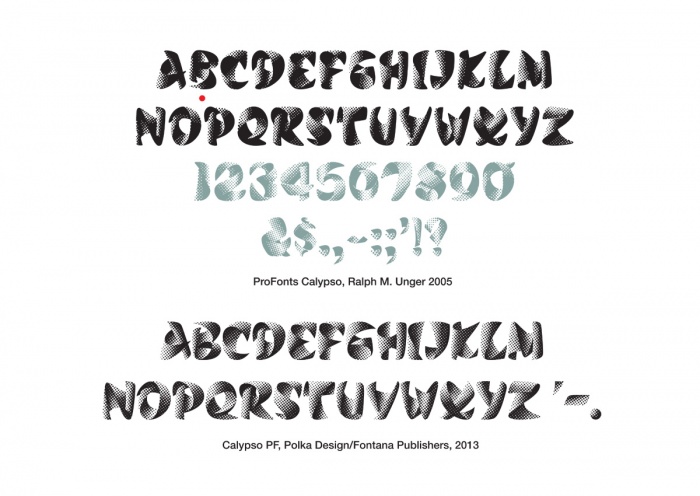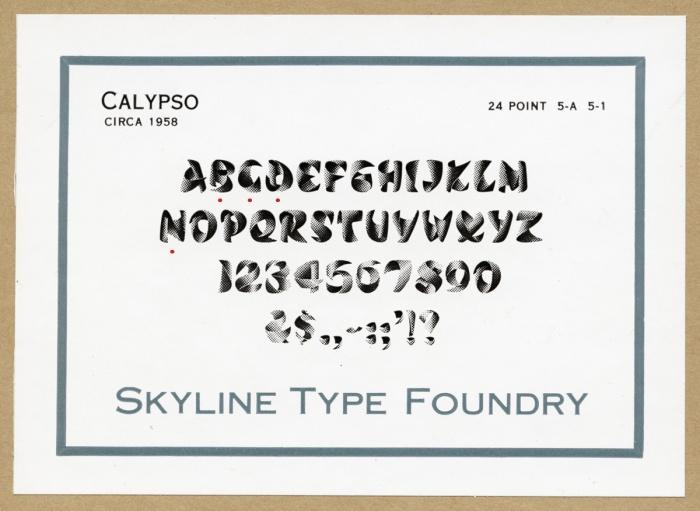
Excoffon's Calypso PF als freier download
Hier noch eine Mikro-Aufnahme von die Calypso ‘A’ links und die Dimension ‘A’ rechts. Ich denke das die Matrizen der Dimension gemacht sind mit das Elektrotypie Verfahren? Oder mit Ätzen auf Basis von Filme die aufgenommen sind von einen Druck der Calypso? Das erklärt dann vielleicht warum manche Letter gedreht sind und Details verschwunden sind?
Dieses zweite Bild zeigt einige Anfürungszeichen der Dimension. Diese sind kreativ fantasiert worden und waren nieTeil der Calypso. Sind auch ugly oder was meint ihr?
So zu sehen habe ich auch was Amerikanischen Schimmel importiert aus der US ...
Um diese Geschichte der Calypso komplett zu machen habe ich drei Versionen aufgereiht in unterstehende Bilder. Oben der Aufkleber auf die Verpackung der 24 pt Calypso/Dimension in Blei von Skyline. Ich habe mit rote Punkte die gespiegelten Lettern angezeigt. In die Version von Ralph M. Unger ist nur noch die ‘B’ gespiegelt. Unger hat aber in mehrere Lettern etwas geändert/verbessert an die Dimension. Er hat die Null etwas geändert während dieser bei Skyline dasselbe ist wie das ‘O’. Die 1 bleibt eine gespiegelte ‘I’. Die 4 hat bei Unger ein Auge bekommen was besser ist in Vergleich mit die Skyline Version. Ich finde auch die 6 von Unger besser passen. An den Druck auf den Aufkleber ist meiner Hinsicht nach aber deutlich zu sehen das die Ergänzungen in Grauwert überhaupt nicht passen bei die schön zu einander passende Buchstaben von Excoffon. Unger hat übrigens noch mehr Buchstaben und Zeichen hinzugefügt die ich nicht aufgenommen habe. Für eine komplette Übersicht siehe: http://www.linotype.com/653967/CalypsoStdRegular-product.html
Auch die Calypso Boy habe ich nicht aufgenommen hier und auch nicht die Blei Version von die original Matrizen von Olive weil ich kein kompletter Druck davon habe.
Ich hatte eigentlich meinen Beitrag über die Calypso letzte Woche abgeschlossen aber ich bekam Heute eine Schriftprobe die ich nicht liegen lassen konnte. Es hat denselben grünen Hintergrund wie die vorher gezeigte Probe von Los Angeles Type Founders die die Matrizen der Typefounders of Phoenix übernommen hatten.
Es ist die Schriftprobe ‘Mr. Antique Volume 10: Ornate & Antique Type’ von Typefounders of Phoenix. Es hat keinen Datum aber ich denke das es stammt aus Anfang Sechziger Jahre. Auf Seite 2 ist erwähnt: ‘Diese Schriften sind aus dem frühen 19. Jahrhundert von die Alten Schriftgiessereien ...’. Und dann folgt eine Liste mit US Schriftgiessereien wie Bruce, Barnhart, Keystone und so weiter. Olive ist nicht erwähnt.
Unter jede Schrift steht der Ursprung der Schrift. Unter die Dimension steht aber: ‘Eine Französische Styling aus dem späten 19. Jahrhundert’. Calypso war zu dieser Zeit aber erst ein par Jahre alt (1958).
Ich finde diese Probe ein Juwel mit die gespiegelte Buchstaben und dazu den Tippfehler in den ersten Satz. Camp from the sixties!
Nachwort #2: Ich war gerade an die Arbeit für mein neues Topic (http://www.typografie.info/3/topic/28947-die-wappen-der-buchgewerbe-%E2%80%93-ein-neues-projekt/) als ich mir realisierte das Excoffon seine Inspiration für die 3D Calypso auch vielleicht gefunden hat in alte Cartouches. Im Bild ist im Buch über Olive und Excoffon (links) eine modernere Interpretation von diese Cartouches zu sehen auf die Umschläge der ersten Schriftproben der Calypso. Diese Cartouches waren 3D gemeinte Zeichnungen als Dekoration für Texte. Die gezeigte Mappe mit 24 Cartouches ist ‘Recueil de Cartouches inventées par Joh. Vredeman de Vriese, ausgegeben in Brussel durch G.A. van Trigt, Éditeur (Verleger) rund 1875.
Nachwort #3: und dann kann ich es natürlich nicht lassen unsere Interpretation mit diese Cartouches sehen zu lassen. Diese Postkarten haben wir gemacht als Beigabe zu die Niederländische Limited Edition von unser Buch Letterfontein in 2009.
Übersetzung in Deutsch: Eine Serife ist ein Buchstabe mit Füße.
Karte für unser Buch Die Musen über Klassische Musik. Übersetzung in Deutsch: Paganini war ein Hardrocker.
Karte für unser Buch Fresh Fonts. Übersetzung in Deutsch: Typografie aus dem Unterleib (richtig übersetzt?)
Karte für unser Buch MiniQuest 01. Übersetzung in Deutsch: Spanjolen (Niederländisch für Butzen, die dunkle Fleckchen auf dem Druckbogen, umringt von einen Halo) kommen aus Spanien.
Die Karten sind gedruckt auf Chromolux Pearl. Die Schrift ist die FF Profile.
Noch ein par Untersuchungen weiter möchte ich meine Meinung die ich am Anfang hatte über das entstehen der Calypso verfeinern. Ich denke das Excoffon sehr bewusst mit diese Papierrolle spielte. Er hatte ein Fascination für 3D Illusionen in die 2D Fläche. Ich denke das er dies auch fand in die oben erwähnte Cartouches. Die  Cartouches die wir verwendet haben für unsere Postkarten sind eigentlich Vorbilder für Architekten wie mann sie schneidet aus Sandstein, Naturstein oder gar Holz. Es ist also nicht gemeint als Endprodukt sowie wir sie verwendet haben.
Die Cartouche war zuerst zu sehen bei den Egyptern die in ihre Hieroglyphen manchmal auch ein runder Rahmen verwendeten wie zu sehen ist in die Abbildung. In Italien während der Renaissance wurden sie neu erfunden und entstand der Name. Cartouche stammt von das Italienische ‘Cartoccio’ das aufgerolltes Papier bedeutet. So wurde ein 3D Form von aufgerolltes Papier oder Leder ausgeschnitten aus Sandstein. Sie wurden als Umrahmung verwendet für ein rundes Fenster, eine Jahreszahl für das entstehen eines Gebäudes oder als Rahmen für ein Text verwendet. Ich denke das hier in die Fascination für Cartouches und die optische 3D Illusion die Enstehung der Calypso liegt.
Ein Vorbild von eine Cartouche in Holz aus Frankreich.
Und vielen Dank für die wunderbare Calypso und den Werdegang zu Deiner digitalisierten Version.
Bemerkenswert dabei auch, die guten Hinweise der Gruppenmitglieder, die Du ganz selbstverständlich erklärst, aufnimmst und weiterverarbeitest.